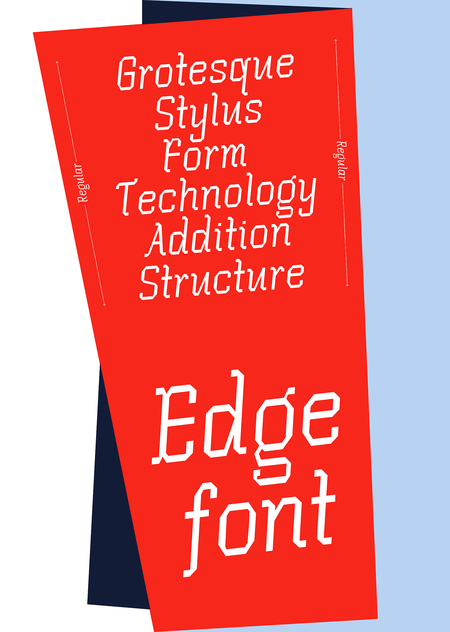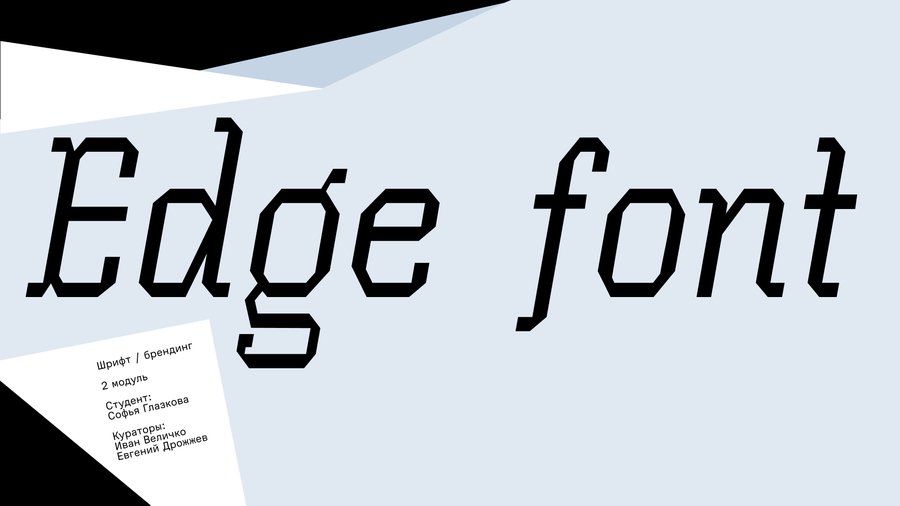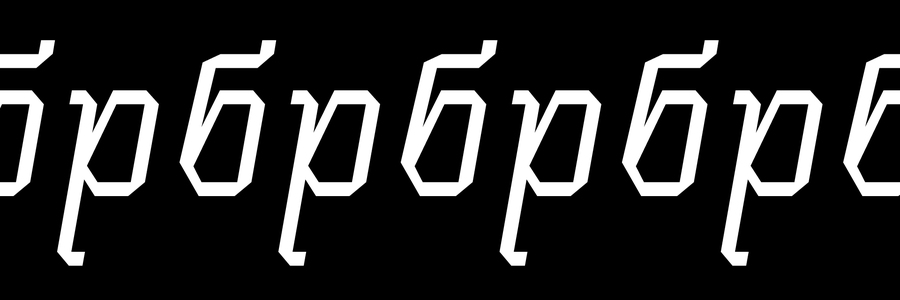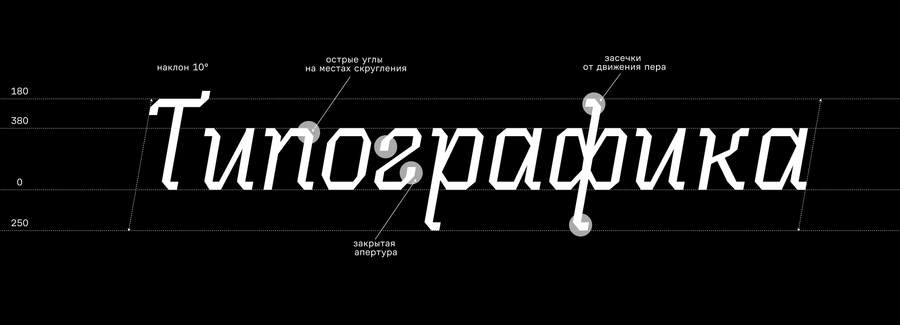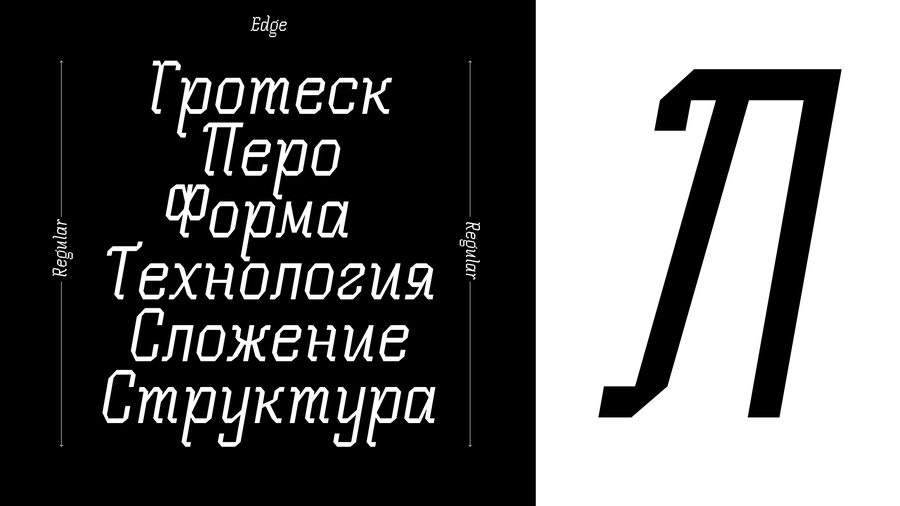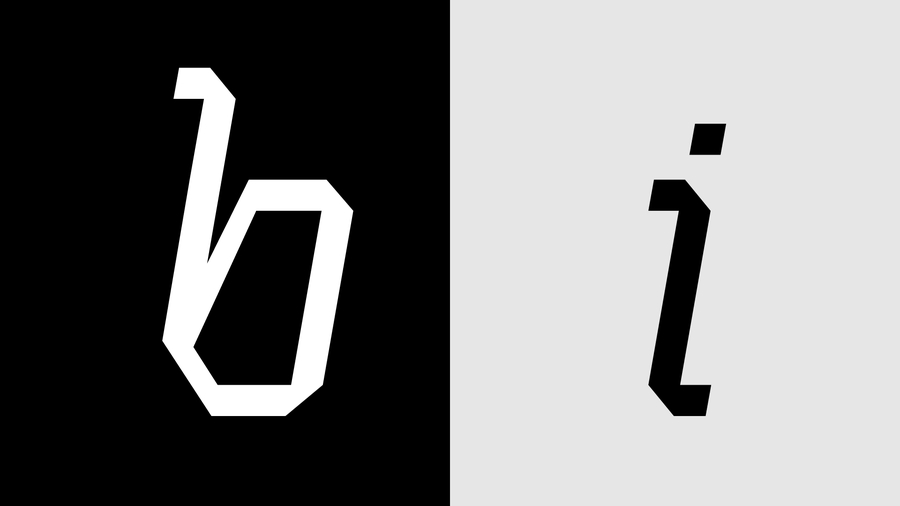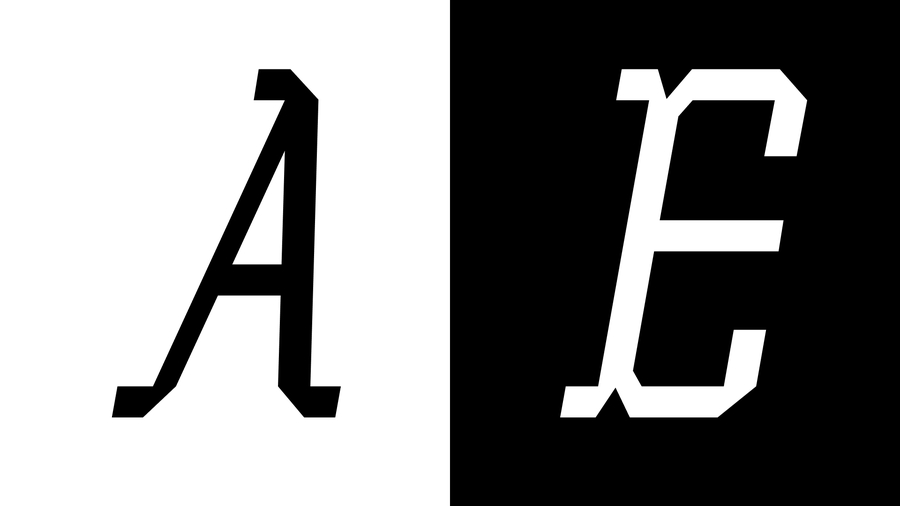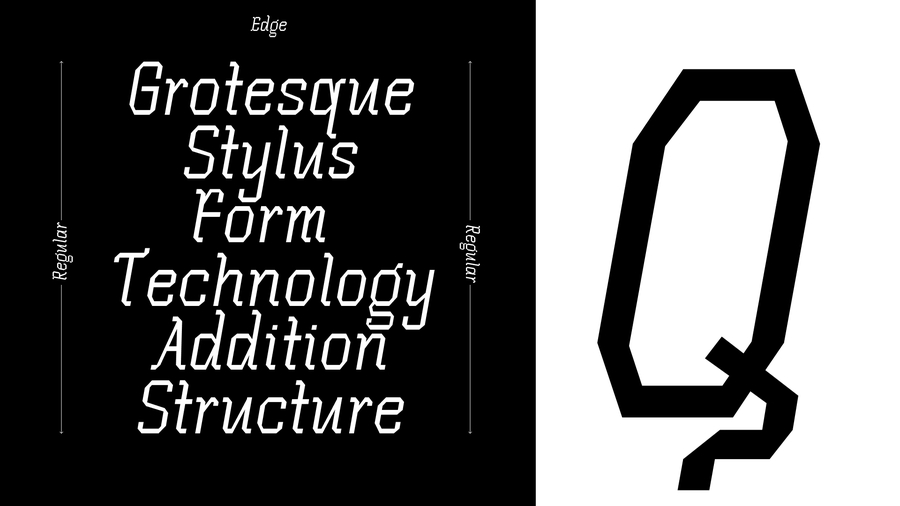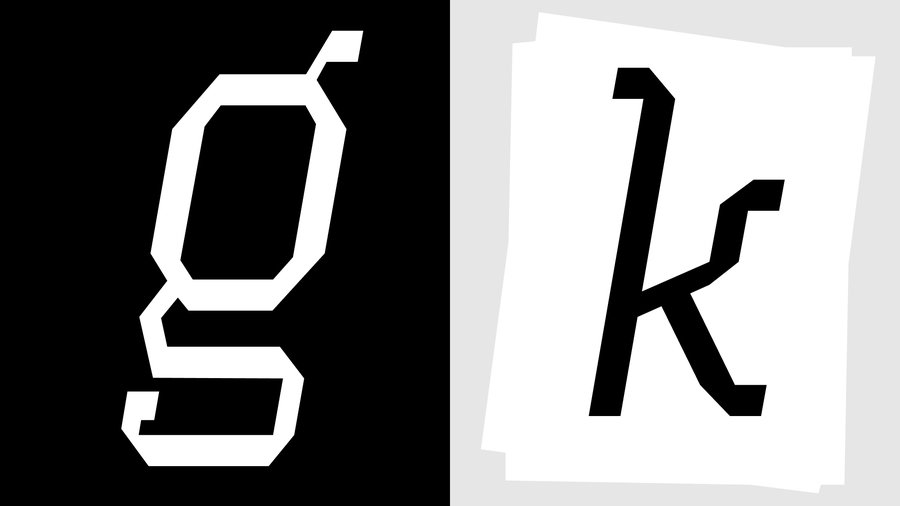
Edge Font
Шрифт переосмысляет рукописную готику от пера. В его основе — характерные угловатые засечки и ломаная пластика готического письма.
В результате возникает гибрид рукописной готики и гротеска — сочетание угловатости, ритма письма и технологичности формы.
К получившемуся шрифту я выбрала мебельный бренд, на стыке дизайна и архитектуры.
В основе — чистые геометрические формы и конструкция. Предметы собираются как пространственные объекты: элементы намеренно смещены, выступают за пределы привычного контура.